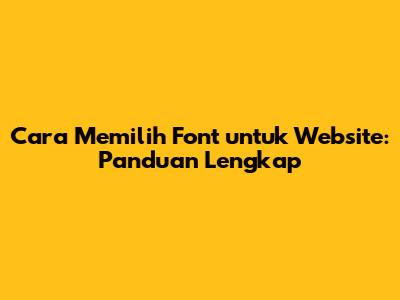
- Jenis Font (Font Families): Ada beberapa kategori utama font, yaitu serif, sans-serif, monospace, cursive, dan fantasy. Masing-masing punya kelebihan dan kekurangan.
- Serif: Font serif punya goresan kecil di ujung huruf (misalnya Times New Roman, Georgia). Cocok untuk teks panjang karena lebih mudah dibaca, terutama di cetakan. Namun, di website, terkadang goresan kecil ini bisa terlihat kurang jelas di layar.
- Sans-serif: Font sans-serif tidak punya goresan (misalnya Arial, Helvetica, Open Sans). Lebih modern dan bersih, cocok untuk tampilan digital. Lebih mudah dibaca di layar dengan resolusi rendah.
- Monospace: Setiap huruf punya lebar yang sama (misalnya Courier New). Biasanya digunakan untuk kode atau teks yang butuh keseragaman.
- Cursive: Meniru tulisan tangan (misalnya Brush Script MT). Cocok untuk tampilan yang lebih kasual atau dekoratif, tapi sulit dibaca untuk teks panjang.
- Fantasy: Font dekoratif yang unik dan menarik (misalnya Comic Sans). Sebaiknya digunakan dengan hati-hati, karena bisa jadi terlalu ramai atau kurang profesional.
- Keterbacaan (Readability): Seberapa mudah teks dibaca. Ini sangat penting untuk website. Font yang sulit dibaca akan membuat pengunjung malas berlama-lama di website kita.
- Keterbacaan (Legibility): Seberapa jelas huruf-huruf dalam font tersebut terlihat. Beberapa font mungkin terlihat bagus, tapi hurufnya sulit dibedakan satu sama lain.
- Ukuran Font (Font Size): Ukuran font yang tepat akan meningkatkan kenyamanan membaca. Terlalu kecil akan sulit dibaca, terlalu besar akan terlihat norak.
- Gaya Font (Font Styles): Tebal (bold), miring (italic), dan garis bawah (underline) bisa digunakan untuk menekankan bagian penting dari teks.
- Spacing: Jarak antar huruf (letter spacing), jarak antar kata (word spacing), dan jarak antar baris (line height) juga penting untuk keterbacaan. Terlalu rapat akan sulit dibaca, terlalu renggang akan terlihat aneh.
Tentukan Tujuan Website: Apa tujuan utama website kita? Apakah untuk menjual produk, memberikan informasi, atau membangun komunitas? Tujuan ini akan mempengaruhi jenis font yang paling cocok.
- Website profesional: Font sans-serif yang bersih dan modern seringkali jadi pilihan yang bagus.
- Blog pribadi: Font serif bisa memberikan kesan yang lebih hangat dan personal.
- Website kreatif: Font yang lebih unik dan menarik bisa jadi pilihan.
Kenali Target Audiens: Siapa target audiens website kita? Usia, minat, dan tingkat pendidikan mereka akan mempengaruhi preferensi font mereka.
- Audiens muda: Font yang lebih modern dan mudah dibaca mungkin lebih cocok.
- Audiens dewasa: Font yang lebih klasik dan profesional bisa jadi pilihan.
Pertimbangkan Brand Identity: Font harus selaras dengan brand identity kita. Jika brand kita ingin terlihat ramah dan ceria, font yang lebih playful mungkin cocok. Jika brand kita ingin terlihat profesional dan elegan, font yang lebih klasik bisa jadi pilihan.
Pilih Font Family: Pilih satu atau dua font family yang cocok dengan tujuan, audiens, dan brand identity kita.
- Google Fonts: Pilihan yang sangat populer karena gratis, mudah digunakan, dan punya banyak pilihan font yang bagus. Contohnya: Open Sans, Roboto, Lato.
- Adobe Fonts: Pilihan berbayar dengan koleksi font yang lebih lengkap dan berkualitas tinggi.
- Font berbayar lainnya: Banyak website yang menyediakan font berbayar dengan kualitas yang sangat baik.
Pilih Kombinasi Font: Jangan gunakan terlalu banyak font yang berbeda. Idealnya, gunakan dua atau tiga font untuk judul, subjudul, dan isi. Pastikan kombinasinya harmonis dan mudah dibaca.
Perhatikan Keterbacaan: Pastikan font yang kita pilih mudah dibaca di berbagai ukuran dan perangkat. Coba lihat website kita di smartphone, tablet, dan komputer.
Uji Coba: Setelah memilih beberapa font, uji coba di website kita. Lihat bagaimana tampilannya, bagaimana keterbacaannya, dan bagaimana pengalaman pengguna secara keseluruhan.
Optimalkan: Sesuaikan ukuran, jarak, dan gaya font sesuai kebutuhan. Pastikan website kita responsif dan terlihat bagus di semua perangkat.
- Open Sans: Sans-serif yang sangat populer di Google Fonts. Mudah dibaca, bersih, dan serbaguna. Cocok untuk berbagai jenis website.
- Kelebihan: Keterbacaan yang sangat baik, tampilan modern, gratis.
- Kekurangan: Mungkin terlihat terlalu umum bagi sebagian orang.
- Roboto: Sans-serif yang juga sangat populer di Google Fonts. Mirip dengan Open Sans, tapi sedikit lebih geometris. Juga sangat mudah dibaca.
- Kelebihan: Keterbacaan yang sangat baik, tampilan modern, gratis, punya banyak variasi gaya.
- Kekurangan: Mungkin terlihat sedikit kurang unik.
- Lato: Sans-serif dengan tampilan yang lebih ramah dan hangat. Sangat cocok untuk website yang ingin memberikan kesan yang lebih personal.
- Kelebihan: Keterbacaan yang baik, tampilan yang ramah, gratis.